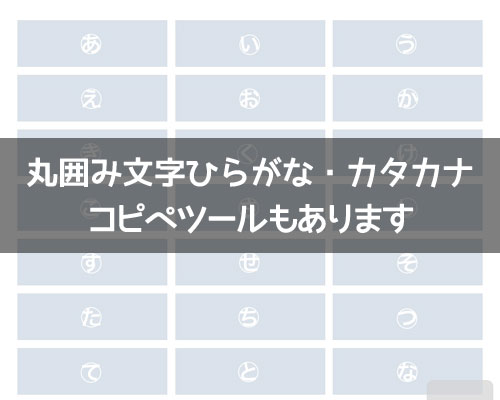
丸囲み文字のひらがなとカタカナ一覧!特殊文字ひらがなをコピペできます 丸囲み文字のひらがなとカタカナ一覧!特殊文字ひらがなをコピペできます
最近のインスタやツイッターでは特殊文字を使って名前やプロフィールを書いてる人が目立ちます。
英語やアルファベットなどの特殊文字は色々あって可愛い文字も多いですが、ひらがなやカタカナの特殊文字ってあまり見かけませんよね。
ひらがなやカタカナの特殊文字で言えば一番有名なのが文字を『○』記号で囲った丸囲み文字です。
丸囲み文字を使ってプロフィールを作りたいけど丸囲み文字の変換方法がわからなくて困っているという方もいるのではないでしょうか。
そこでこのページではひらがなとカタカナの特殊文字である『丸囲み文字』を一覧で用意しました。
ひらがなやカタカナの特殊文字を使いたい方はこちらからコピペして自由にお使いください。
丸囲み文字のひらがな一覧(特殊文字)
以下は特殊文字の丸囲み文字ひらがな一覧です。
あ⃝い⃝う⃝え⃝お⃝
か⃝き⃝く⃝け⃝こ⃝
さ⃝し⃝す⃝せ⃝そ⃝
た⃝ち⃝つ⃝て⃝と⃝
な⃝に⃝ぬ⃝ね⃝の⃝
は⃝ひ⃝ふ⃝へ⃝ほ⃝
ま⃝み⃝む⃝め⃝も⃝
や⃝ゆ⃝よ⃝
ら⃝り⃝る⃝れ⃝ろ⃝
わ⃝を⃝ん⃝
丸囲み文字のカタカナ一覧(特殊文字)
以下はカタカナを丸囲みした特殊文字の一覧です。
㋐㋑㋒㋓㋔
㋕㋖㋗㋘㋙
㋚㋛㋜㋝㋞
㋟㋠㋡㋢㋣
㋤㋥㋦㋧㋨
㋩㋪㋫㋬㋭
㋮㋯㋰㋱㋲
㋳㋴㋵
㋶㋷㋸㋹㋺
㋻㋾ン⃝
ひらがなと同様に、カタカナを四角囲みした特殊文字もあります。
丸囲み文字以外のひらがなとカタカナ特殊文字を使いたい時
ひらがなもカタカナも丸囲み文字は意外と多くの方が使っている特殊文字ですが、実は囲み文字以外の特殊文字もあったりします。
例えば、下線やドットは定番として、珍しい星マークやニコちゃんマークのような顔文字付きの特殊文字などもあります。
【星マーク】
あ͙い͙う͙え͙お͙
【顔文字】
ア̤̫イ̤̫ウ̤̫エ̤̫オ̤̫
このような少し珍しい特殊文字は他にも色々あって、専用のツール(もじつく)を使えば自分で好きなように特殊文字を作る事もできます。
インスタで丸囲み文字を活用する方法
インスタグラムの投稿やプロフィールに丸囲み文字を使うと個性を際立たせることができます。
特にストーリーズやキャプションで使うと目を引きやすくなりフォロワーの注目を集められるでしょう。
このセクションでは実際にどのように丸囲み文字を活用できるかを解説します。
具体的なシーン別の使用方法や注意点を参考にして自分だけのオリジナルスタイルを作りましょう。
プロフィール・投稿での映える使い方
インスタプロフィールでは名前や説明文に丸囲み文字を加えることで目立たせることができます。
たとえば、「好きなこと【🍓趣味】」など、要点を囲んだり装飾を組み合わせて強調しましょう。
また、投稿のキャプションで特別な言葉を丸囲み文字にすると強調したい情報を目立たせる効果があります。
ハッシュタグや説明文に使用すると視覚的な違いを生むことができますが使いすぎには注意が必要です。
丸囲み文字が表示されない場合の対処法
丸囲み文字は一部の古い端末や特定のフォント環境では正しく表示されないことがあります。
そのため表示されるか不安な場合は事前に複数のデバイスで確認するのがおすすめです。
またWebフォントに依存するサイトやSNSプラットフォームによっても再現性が異なるため汎用性の高い文字を優先的に使うと安心です。
どうしても表示が不安定な場合は代替文字や絵文字を組み合わせるなどの工夫で視認性を補うことができます。
読者の環境を考慮した丁寧な装飾を心がけましょう。
まとめ
ひらがなやカタカナの特殊文字は英語と比べると数も少なくて少し見劣りする部分もありますが、日本人としてはひらがなやカタカナもオシャレに使いたいですよね。
もじつくでひらがなやカタカナを使って新しい特殊文字を作れば丸囲み文字以外の特殊文字も広がっていきそうです。